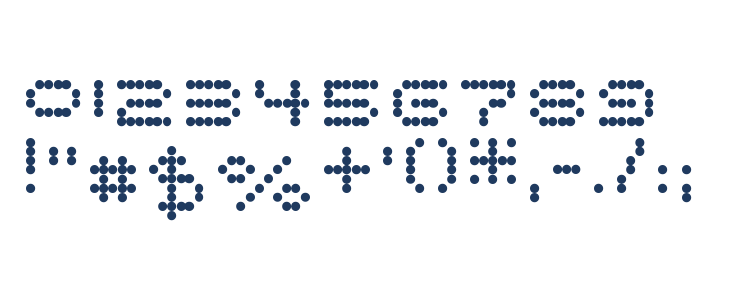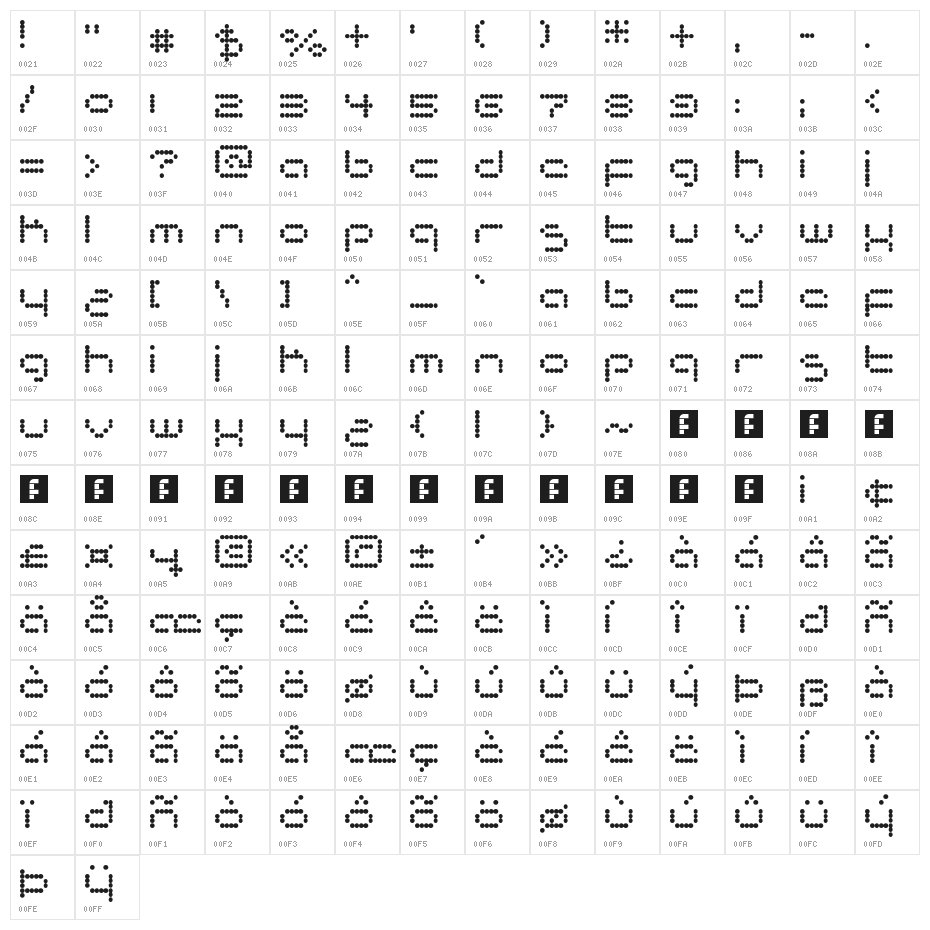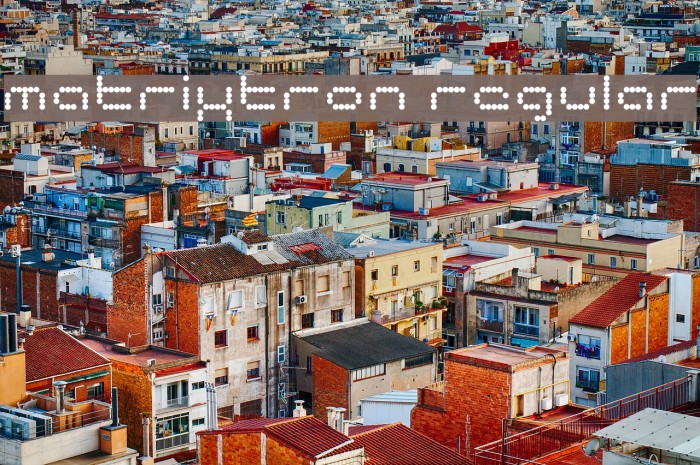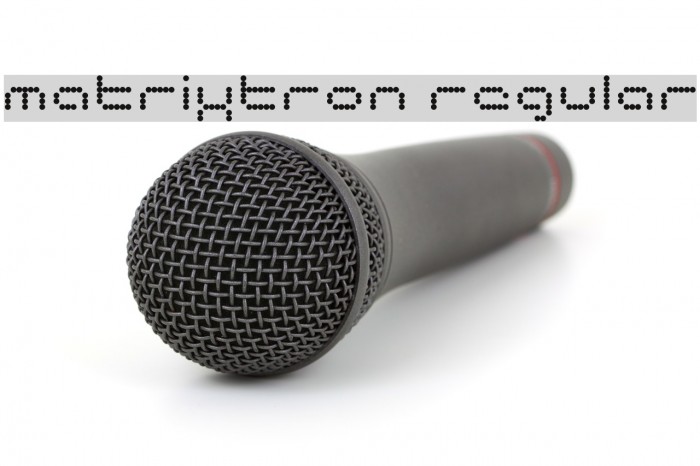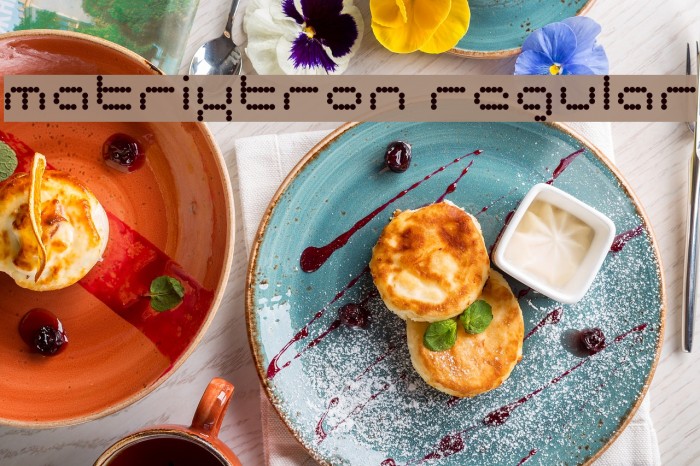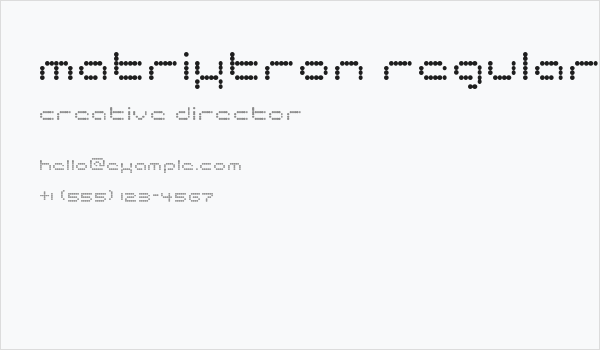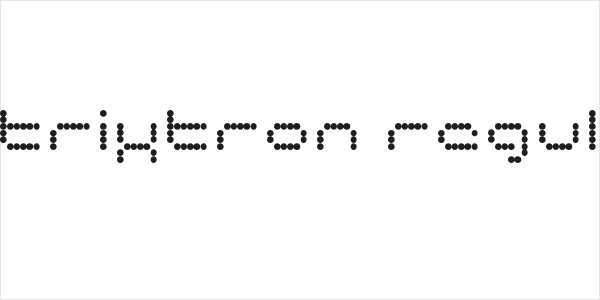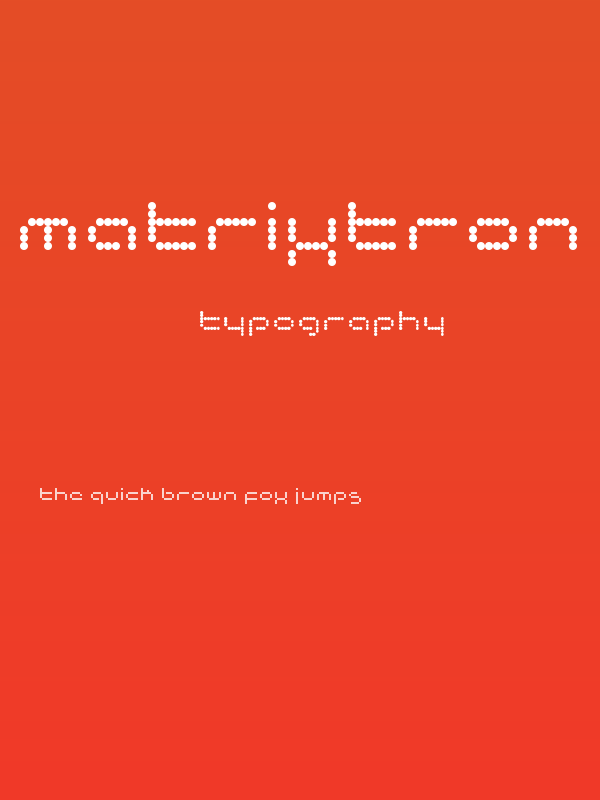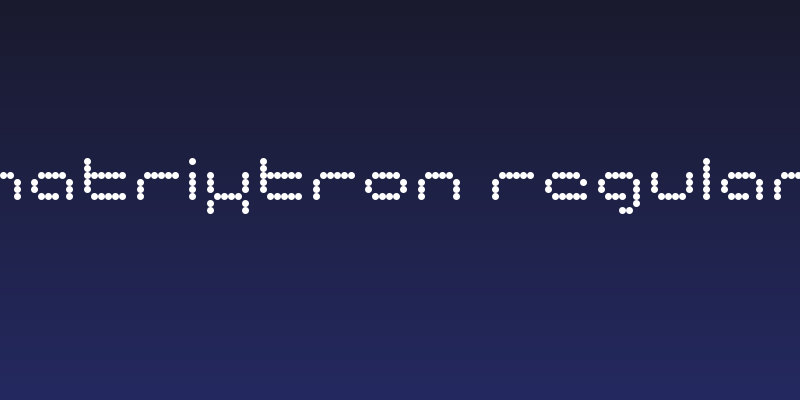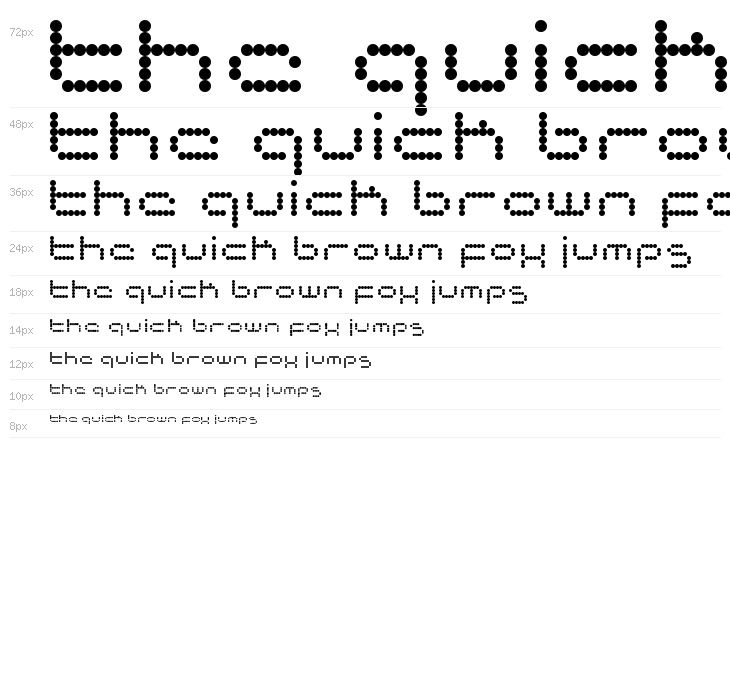
matrixtron Regular Font
| Stile generale | Modern, Vintage |
| Caso d'uso | Logos, Headlines, Digital displays |
| Progetti proposti | Ideal for digital-themed projects, tech-related branding, retro gaming interfaces, and futuristic design elements. |